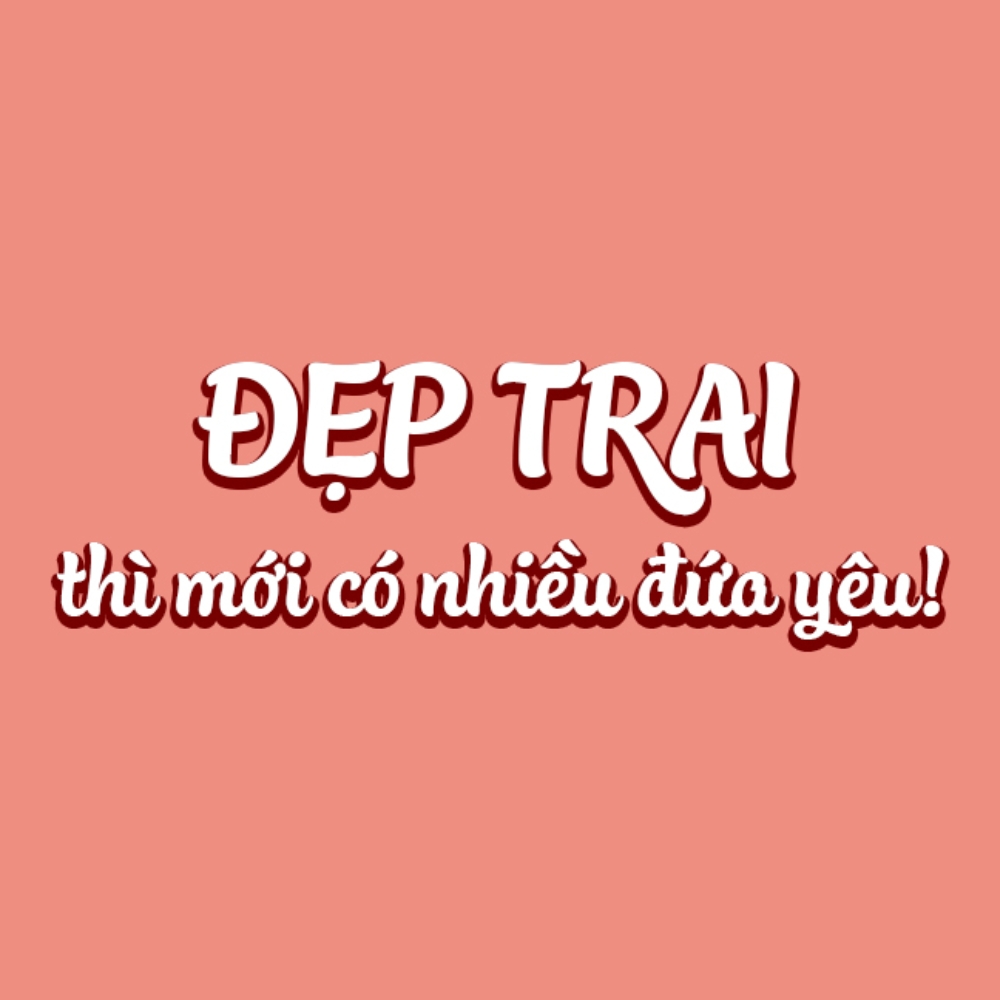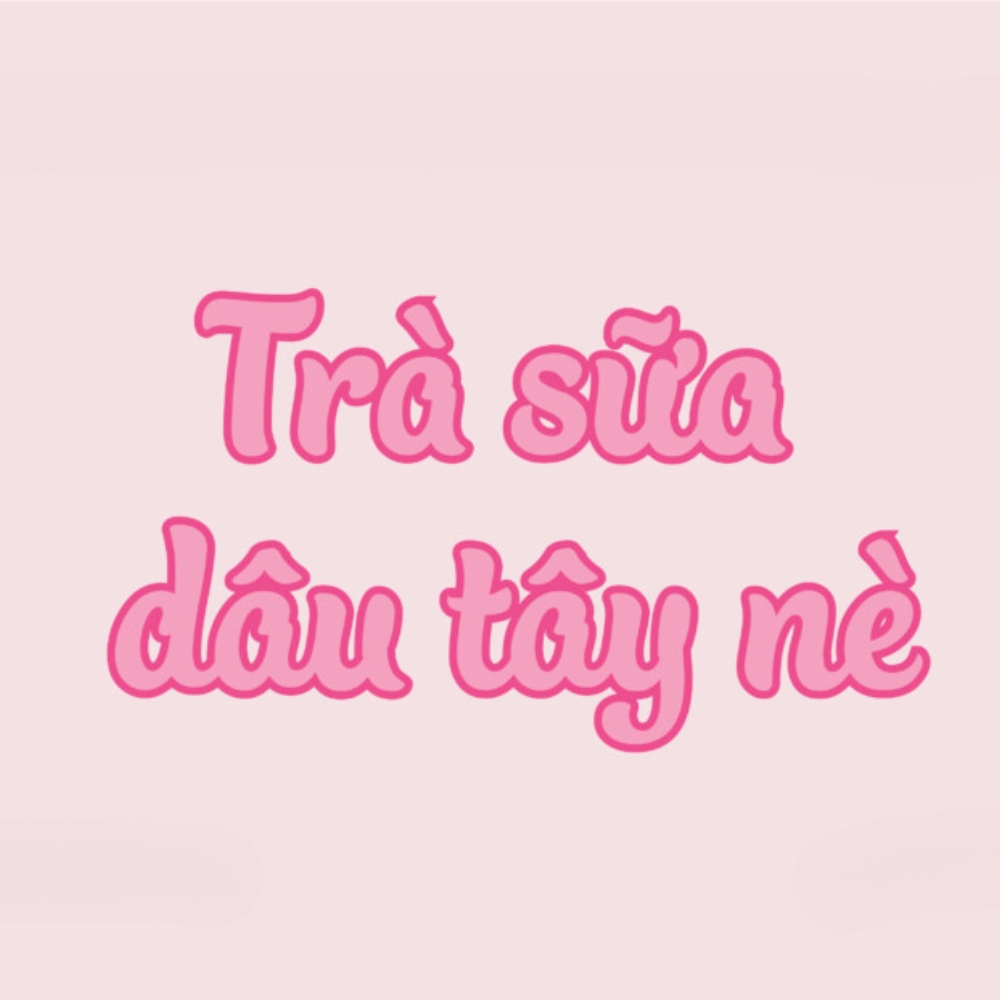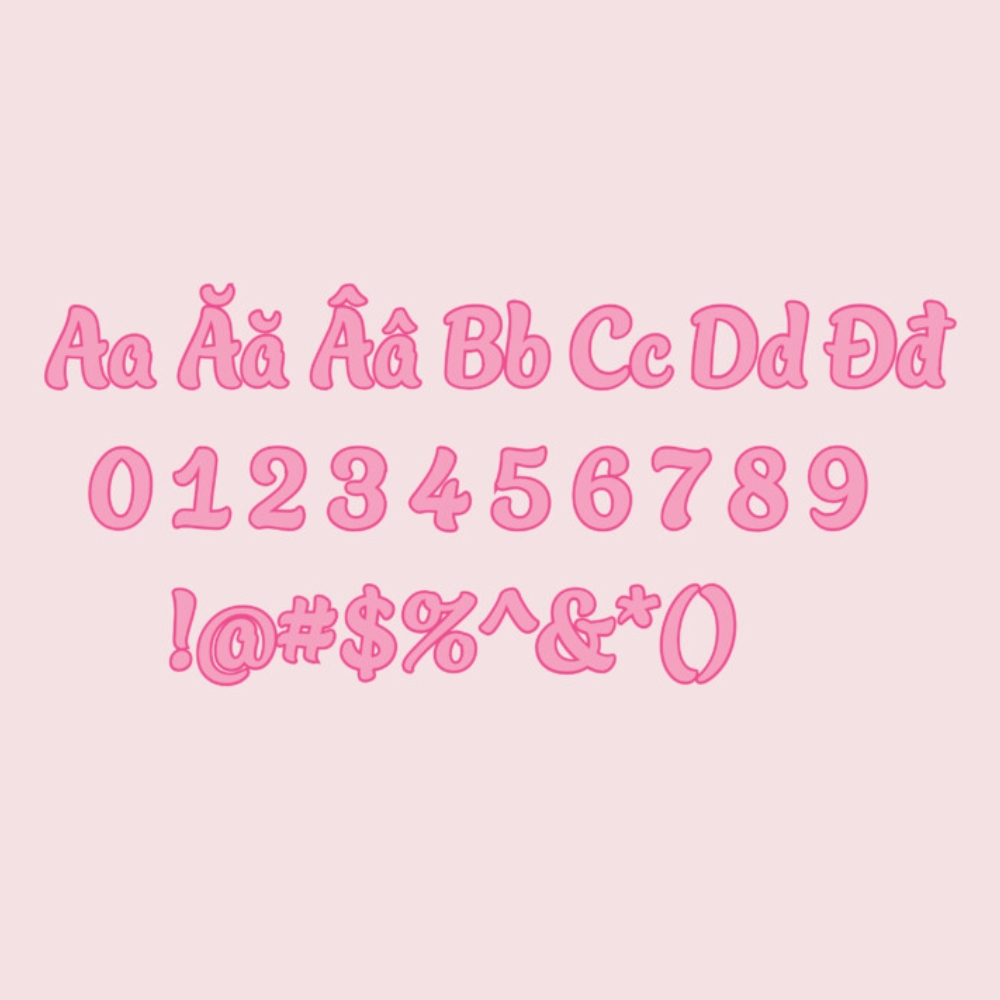
Font chữ SVN-Bali Script việt hoá là font script mang hơi thở của những bảng chỉ dẫn viết tay tại các quán bar bãi biển và surf shack Indonesia phóng khoáng, đương đại và dễ ứng dụng cho thiết kế thương hiệu lifestyle. Bài viết này, In Viva sẽ cung cấp link tải font SVN Bali Script Việt hóa và hướng dẫn dùng đúng cách.
Tải font chữ SVN-Bali Script Việt hóa miễn phí đầy đủ định dạng là lựa chọn lý tưởng cho những ai đang tìm kiếm một font chữ viết tay mềm mại, sang trọng để thiết kế logo, thiệp cưới hoặc tiêu đề nổi bật. Với nét chữ uốn lượn đặc trưng và hỗ trợ tiếng Việt đầy đủ, Bali Script giúp sản phẩm thiết kế trở nên tinh tế và chuyên nghiệp hơn chỉ trong vài bước cài đặt.
Đặc điểm của font SVN Bali Script
SVN Bali Script do Dave Rowland thiết kế, phát hành bởi Schizotype, Việt hóa bởi STYLEno.1 Fonts. Font thuộc nhóm script chữ viết tay cách điệu theo phong cách baseball script đương đại.
- Phong cách beach casual: Lấy cảm hứng từ bảng chỉ dẫn viết tay tại các quán bar bãi biển và lều lướt sóng Bali, nét chữ có độ phồng ở cuối nét, gooey và táo bạo hơn baseball script thông thường.
- Có thêm bản Highlight: Bộ gốc đi kèm Bali Script Highlight có lớp phủ tạo hiệu ứng bóng bẩy, hoạt hình khi overlay lên chữ chính, đặc biệt phù hợp cho logo.
- Chỉ có Regular, không có weight phụ: Toàn bộ cá tính của font nằm ở dáng chữ và chi tiết nét không thể làm đậm hay nghiêng thêm.
- Bản Việt hóa hỗ trợ Unicode: STYLEno.1 Fonts bổ sung đầy đủ ký tự tiếng Việt có dấu theo chuẩn Unicode, dùng được ngay mà không cần chuyển đổi bảng mã.
Ứng dụng của font chữ SVN-Bali Script việt hóa trong thiết kế
Bali Script phát huy tốt nhất trong các thiết kế cần cảm giác tự nhiên, phóng khoáng và mang hơi thở lifestyle không phải font cho mọi thương hiệu.
- Logo và wordmark thương hiệu F&B, surf, resort: nét script phồng và táo bạo của Bali Script tạo ra logo có cá tính rõ ràng, phù hợp với quán cà phê bãi biển, thương hiệu thức uống hoặc resort lifestyle.
- Packaging sản phẩm nước giải khát, kem, bánh kẹo: phối Bali Script với sans-serif nhẹ cho thông tin phụ tạo ra bao bì trông thủ công và thân thiện.
- Tiêu đề poster sự kiện mùa hè, festival âm nhạc: cỡ lớn từ 60pt trở lên, font hiện rõ chi tiết nét và tạo điểm nhấn mạnh trên mặt poster.
- Thiệp mời, menu nhà hàng phong cách casual: kết hợp Bali Script cho tên món hoặc tiêu đề với font serif nhẹ cho mô tả tạo ra hệ thống chữ cân bằng giữa cá tính và dễ đọc.
Lỗi thường gặp khi dùng font SVN Bali Script
Khi sử dụng font chữ SVN-Bali Script việt hóa nhiều designer và người làm in ấn thường gặp phải một số lỗi phổ biến sau. Hiểu rõ các lưu ý này sẽ giúp bạn tránh sai sót, tiết kiệm thời gian và đảm bảo sản phẩm cuối cùng đẹp mắt, chuyên nghiệp hơn.
- Dùng Bali Script cho nội dung dài hơn một dòng. Font script có độ nghiêng và nét nối giữa các ký tự, dễ đọc ở 1–3 từ tiêu đề nhưng mất khả năng đọc nhanh khi dùng cho đoạn văn. Chỉ dùng cho tên thương hiệu, tagline hoặc tiêu đề ngắn.
- Không thử Bali Script Highlight khi làm logo. Nhiều designer chỉ dùng bản chính và bỏ qua layer Highlight đi kèm. Overlay hai lớp với màu sắc khác nhau tạo hiệu ứng bóng bẩy rất đặc trưng, khó đạt được bằng các kỹ thuật hậu kỳ thông thường.